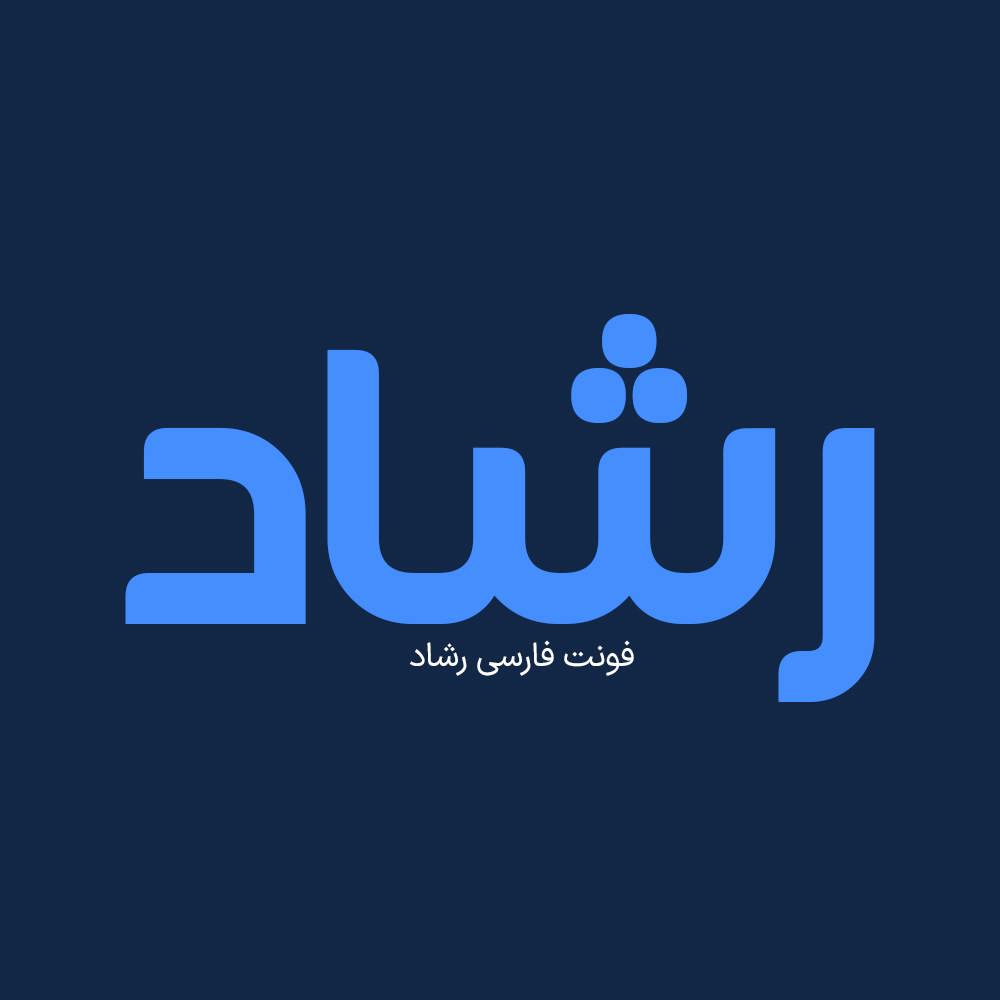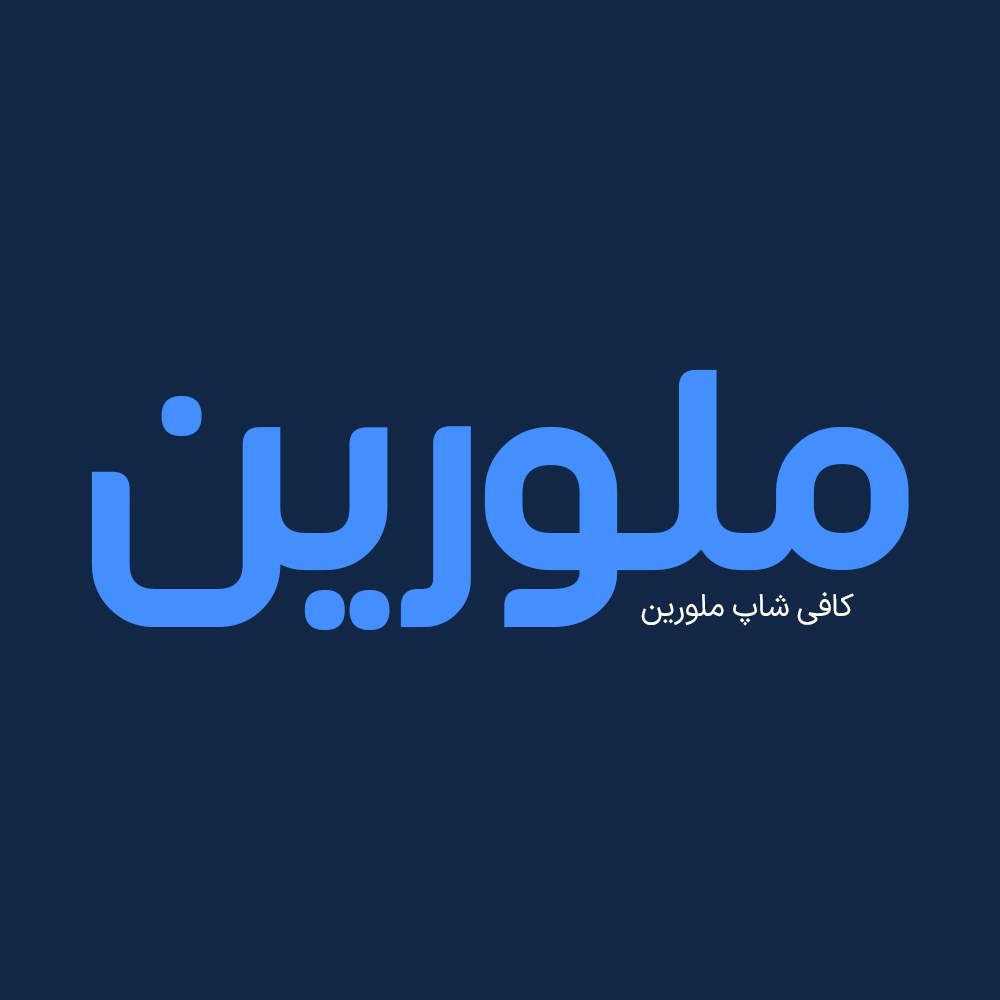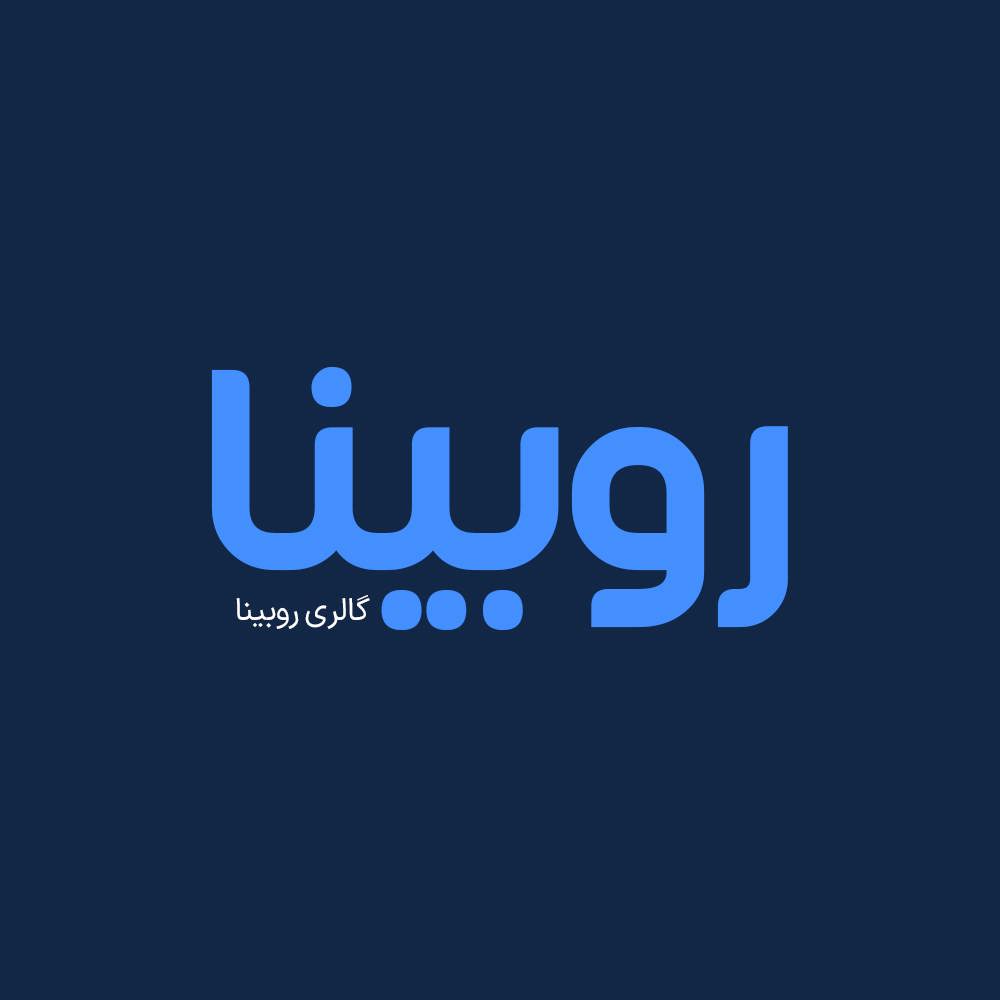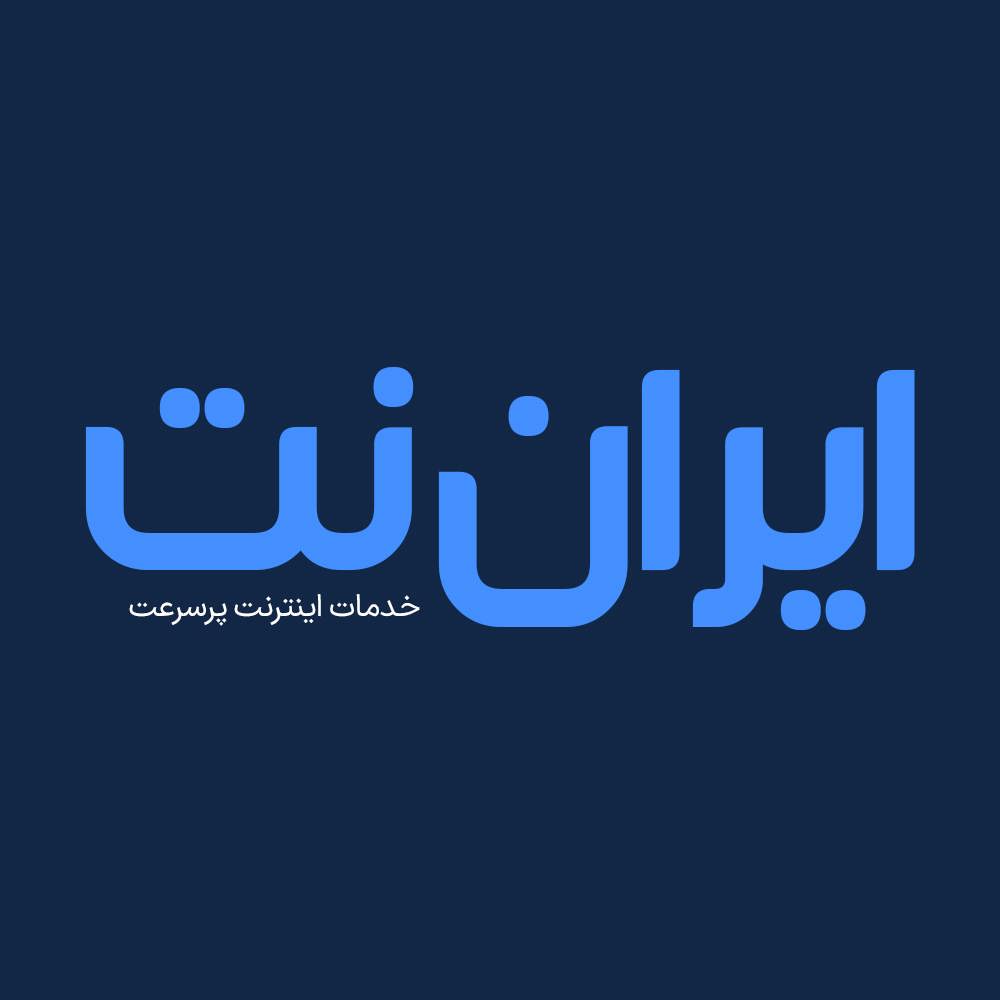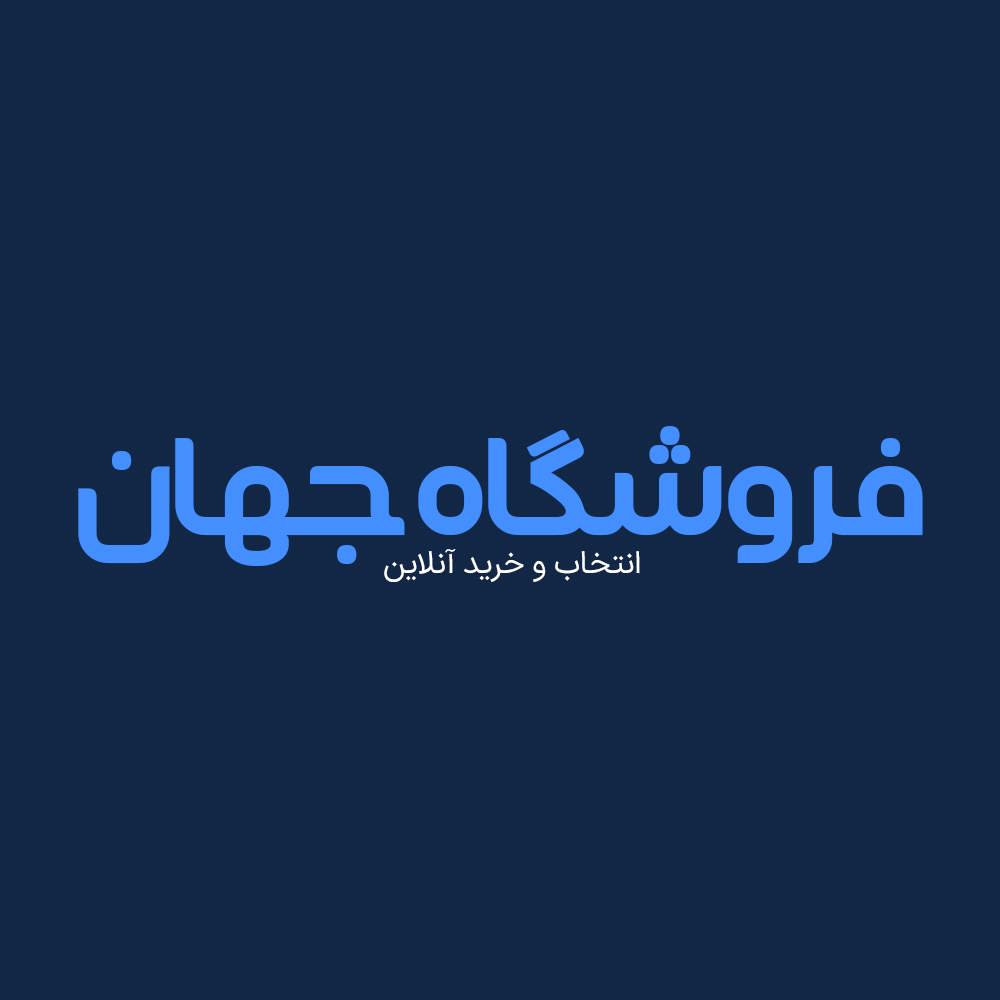
فونت فارسی رشاد Reshad Font
فونت فارسی رشاد یک فونت تک وزن با کاربرد طراحی لوگوتایپ و طراحی های مختلف همچون کتاب و تولید محتوای متن های کوتاه و عناوین می باشد. این فونت با ساختار حروف خود مناسب استفاده در لوگوهای نوشتاری می باشد. فونت رشاد با تعادل عادلانه ای که بین شکل انسانی حروف و جنبه هندسی آن ترکیب می کند، به ویژگی کاریزماتیک خود دست می یابد. همچنین از این فونت در طراحی تابلوهای چلنیوم هم به دلیل ساختار منحصر به فردش می توانید استفاده کنید. در ادامه برای شما نمونه تایپ های این محصول حرفه ای رو آماده کردیم که میتونید مشاهده کنید.
• مناسب طراحی بسته بندی ها و چاپ
• فونت ویژه تبلیغات محیطی
• فونت طراحی کاور اینستاگرام
• فونت حرفه ای برای تولید محتوا
• فونت فارسی طراحی وبسایت
• فونت طراحی لوگو تایپ فارسی
• مناسب استفاده در تابلو های چلنیوم و طراحی حروف
پیشنمایش و نمونه تایپ های فونت رشاد